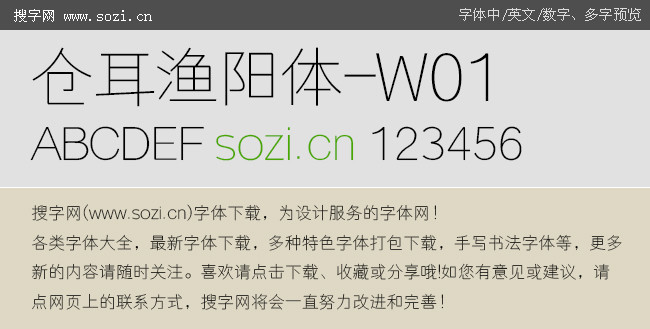
站酷倉(cāng)耳漁陽(yáng)體-W01
搜字網(wǎng)提供一款站酷倉(cāng)耳漁陽(yáng)體-W01中文藝術(shù)字體下載,站酷倉(cāng)耳漁陽(yáng)體字形結(jié)合宋、黑二體的結(jié)構(gòu)特點(diǎn),將部分筆畫(huà)轉(zhuǎn)折處做圓角處理,方圓結(jié)合,厚重又不失靈動(dòng)。家族字體包含5個(gè)字重,均可免費(fèi)商用。